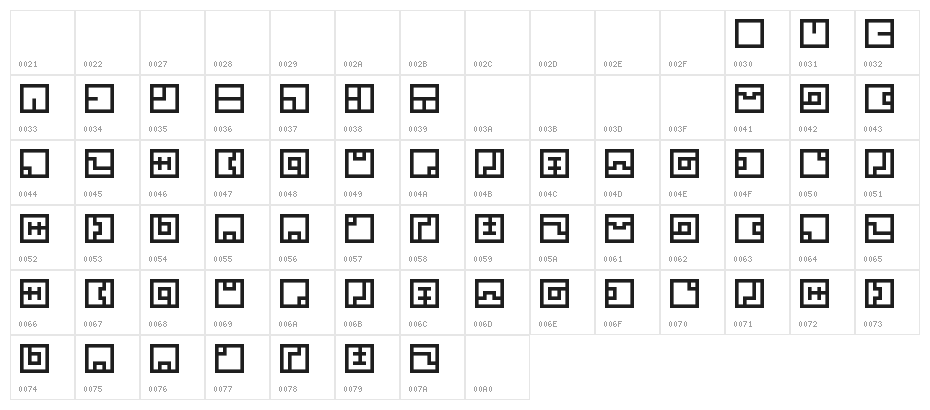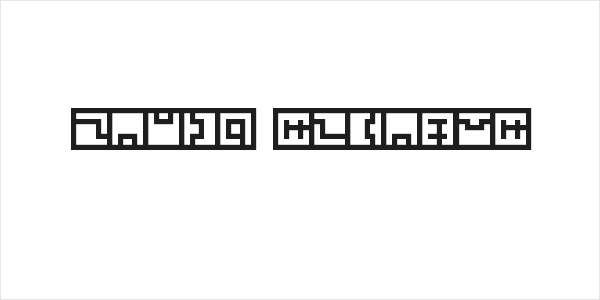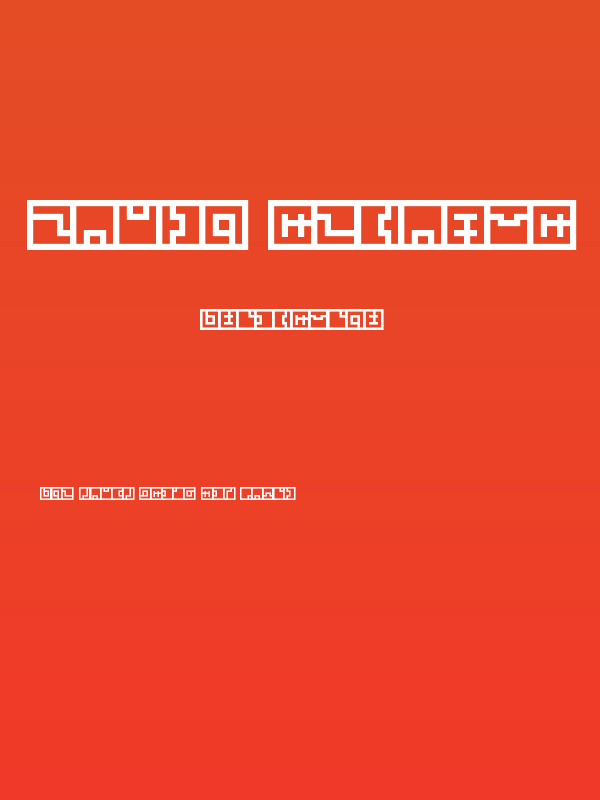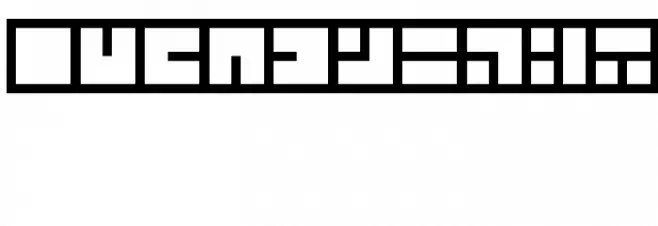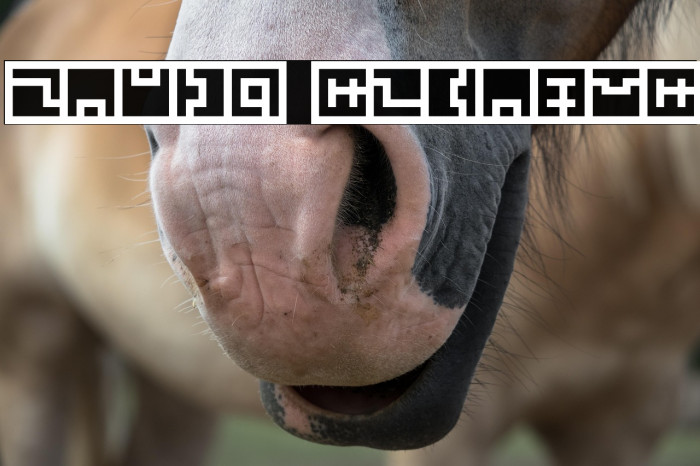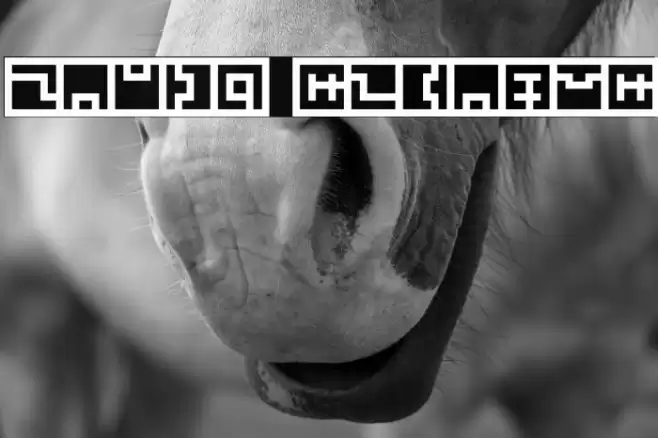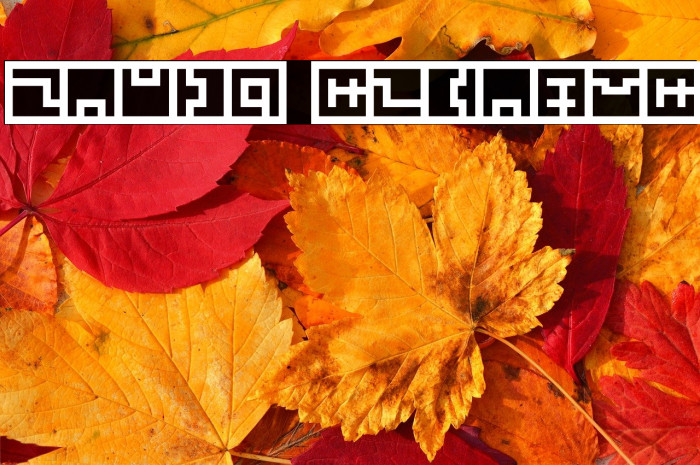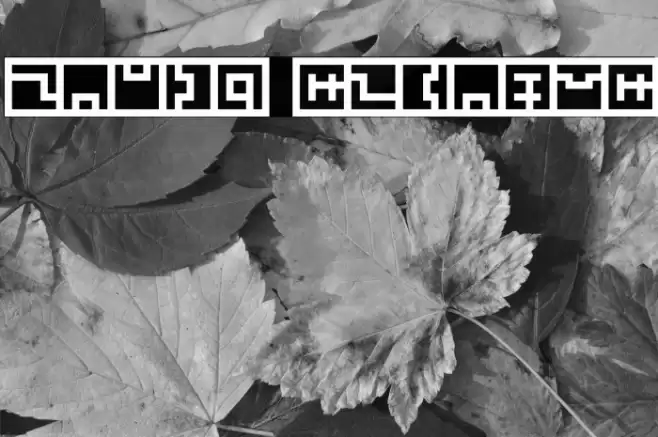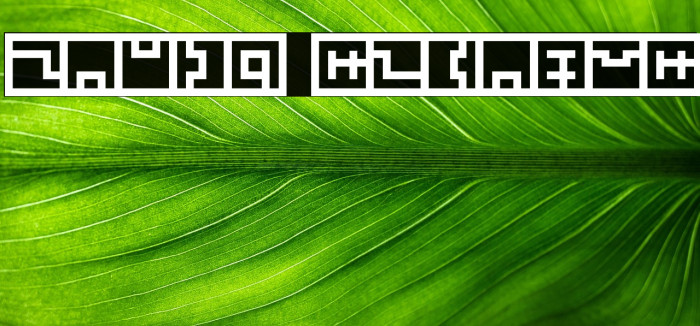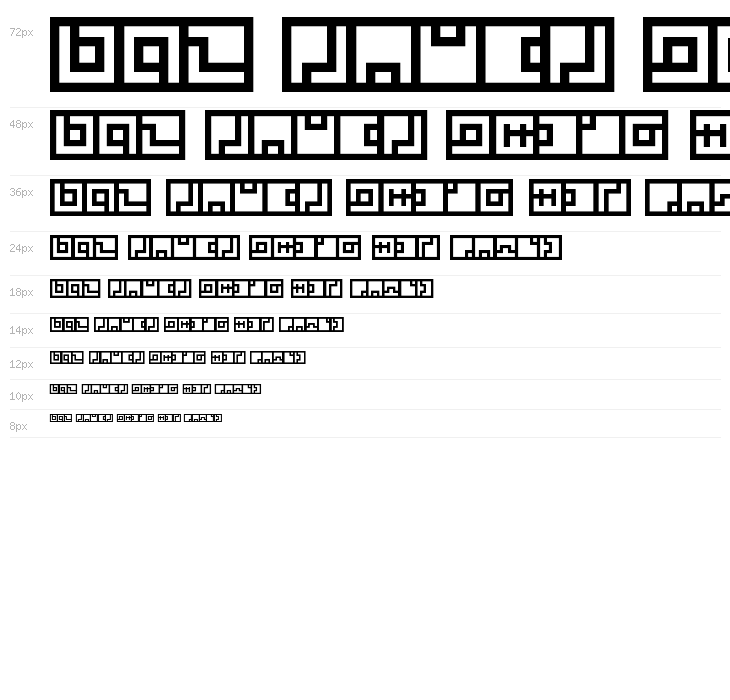
Zuish Regular Font
✎ Pixel
| Kategorien | Pixel |
| Anwendungsfall | Logos, Headlines, Posters |
| Vorgeschlagene Projekte | Ideal for digital art, video game design, futuristic branding, and creative posters. |